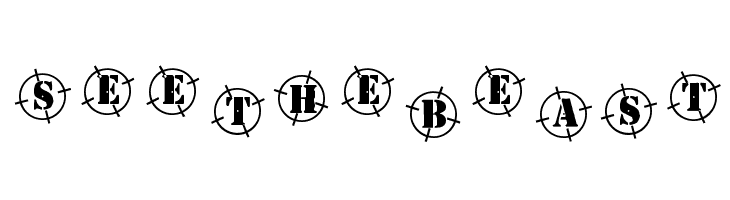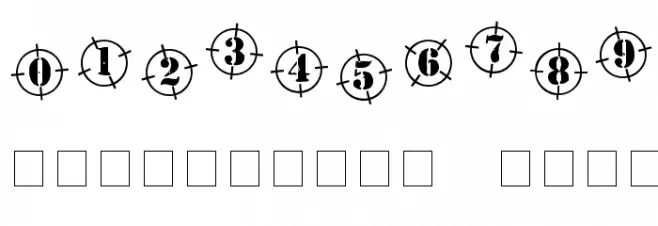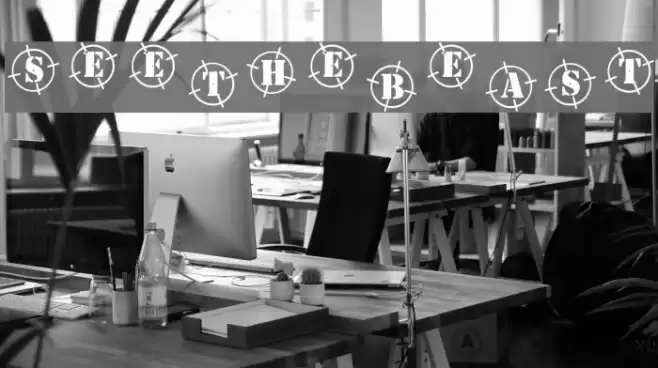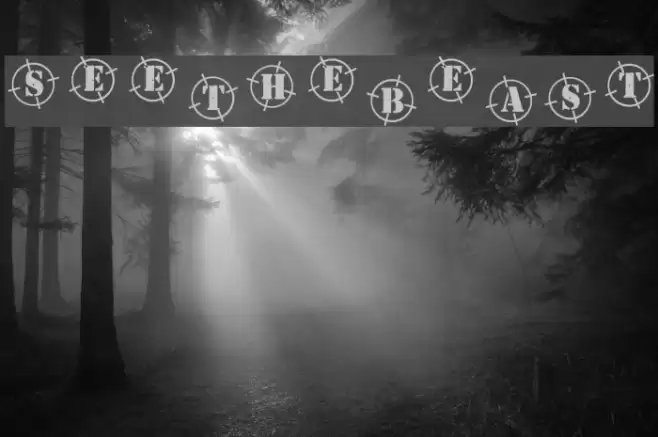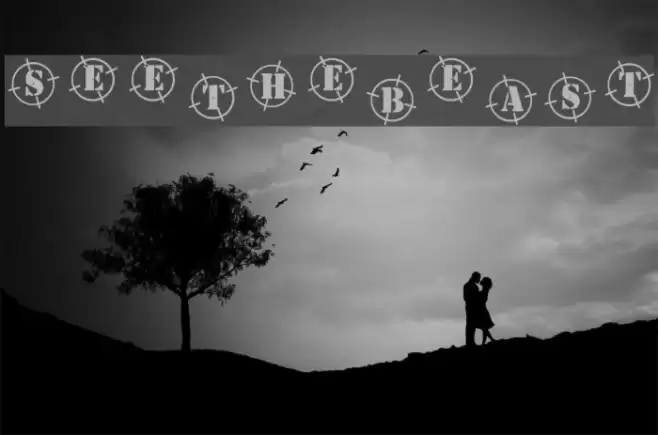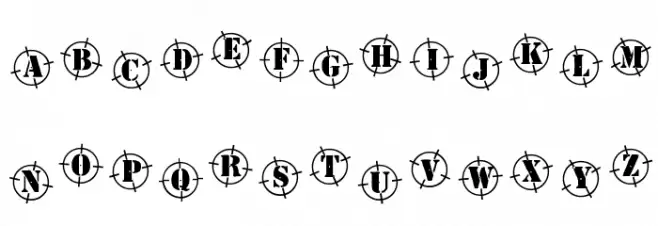
SeeTheBeast Font
| Progetti proposti | Ideal for military-themed designs, video game graphics, posters, and branding that requires a bold statement. |